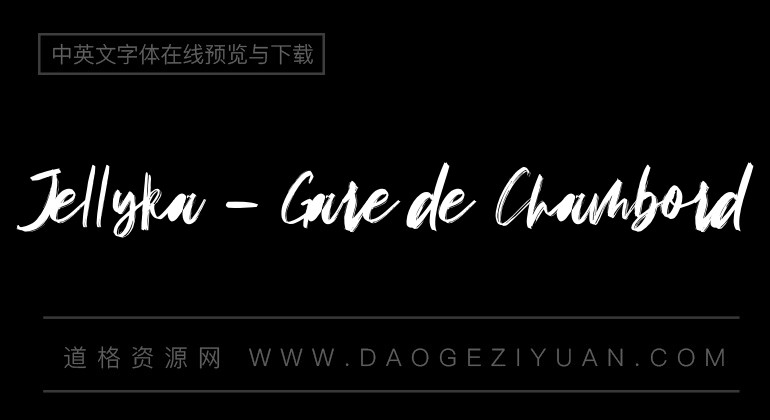
Jellyka - Gare de Chambord
Jellyka - Gare de Chambord 字体是一款古典风格的草书字体,它的笔画精致优雅,拥有流畅的轮廓,令人眼前一亮。字体的特点是有一定的视觉冲击力,而且还能够体现出古典风格的优雅气质。它也有着细腻的笔画,使得文字更加显得优美大方。Jellyka - Gare de Chambord 字体可以用于各种印刷品、广告、海报、书籍封面等,能够给读者带来古典风格的视觉享受。
Jellyka - Gare de Chambord是一款非常不错的手写艺术字体,具有很好的视觉感,适合于文化类的宣传设计、商业类品牌的广告和产品包装设计以及个性化文字排版等较多场景。